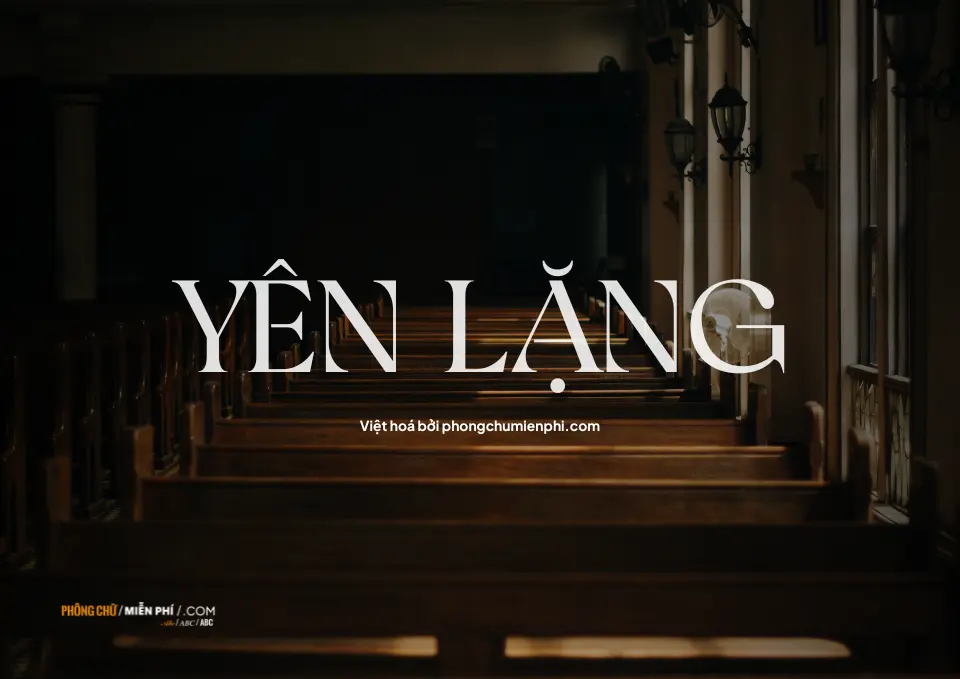
Font Việt hoá PCMP Binerka
PCMP Binerka có thể được mô tả là một phông chữ serif thanh lịch và đẹp mắt. Nó nổi bật trong bất kỳ bối cảnh nào cần những nét cá nhân, chẳng hạn như thiệp mời đám cưới, thiệp cảm ơn, thiệp cưới, thiệp chúc mừng doanh nghiệp, thiệp chúc mừng và các ứng dụng tương tự khác.